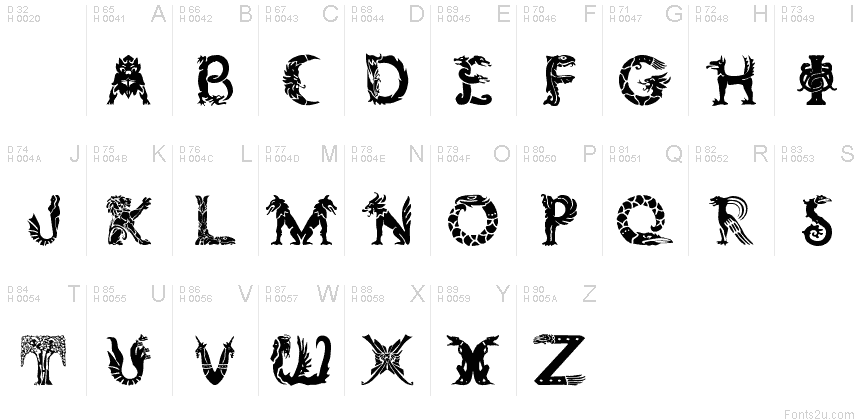
Zoomorphica, di David F. Nalle di Scriptorium Fonts, è un carattere display zoomorfo gratuito che evoca le iniziali miniate che si trovano nei margini dei bestiari medievali. Le lettere appaiono inizialmente come forme nere audaci, per poi rivelare dettagli animali e piume lavorate nelle estremità, rendendo il font un ibrido tra un segno grafico e un emblema.
È la scelta ideale per copertine di libri fantasy, titoli di videogiochi, poster, capilettera e monogrammi in cui basta una sola lettera a creare l'atmosfera. Come carattere gratuito per nomi brevi o iniziali, aggiunge una nota medievale ed araldica senza bisogno di ulteriori ornamenti.